Tải 10+ Font Chữ Việt Hóa Phong Cách Xưa, Hơi Thở Hoài Cổ Dành Cho Designer
Trong thời đại số hóa và hiện đại hóa, khi mà các xu hướng thiết kế ngày càng trở nên sắc sảo, tối giản và phẳng, thì phong cách hoài cổ (vintage) lại có một chỗ đứng vững chắc và không hề bị lãng quên. Một trong những yếu tố then chốt giúp tái hiện tinh thần xưa cũ trong thiết kế chính là font chữ phong cách xưa, đặc biệt là các font chữ Việt hóa – vốn giúp người Việt dễ dàng tiếp cận và sử dụng trong các sản phẩm thiết kế mang màu sắc bản địa.
Font Chữ Phong Cách Xưa Là Gì?
Font chữ phong cách xưa thường lấy cảm hứng từ kiểu chữ được sử dụng trong các thập niên trước, như thời kỳ Đông Dương, những năm 50 – 70 tại Việt Nam, hoặc thời kỳ bao cấp. Những font này thường mang đặc trưng:
Đường nét uốn lượn mềm mại hoặc gãy gọn như máy đánh chữ.
Kiểu chữ serif cổ điển hoặc sans-serif dày nét.
Có tính thủ công, cảm giác được in từ máy in typo cũ.
Tái hiện không khí bảng hiệu cũ, bìa báo xưa, sách giáo khoa, tem phiếu thời bao cấp.
Ứng Dụng Của Font Việt Hóa Phong Cách Xưa
Các font chữ này đặc biệt phù hợp với những thiết kế mang hơi thở truyền thống hoặc hoài niệm:
Thiết kế bao bì sản phẩm thủ công, đặc sản vùng miền.
Poster phim xưa, sách báo cổ, tư liệu lịch sử.
Thời trang retro, vintage.
Biển hiệu quán cà phê, tiệm ăn theo phong cách hoài cổ.
Dự án nghệ thuật, triển lãm văn hóa.
Font chữ Việt hóa phong cách xưa không chỉ là công cụ thiết kế, mà còn là cầu nối giúp thế hệ hôm nay chạm đến những giá trị ký ức của ngày hôm qua. Trong thời kỳ công nghệ phát triển như hiện nay, việc sử dụng những font chữ hoài cổ một cách sáng tạo và có chọn lọc sẽ giúp sản phẩm thiết kế mang bản sắc, chiều sâu và cảm xúc – những yếu tố ngày càng được đề cao trong truyền thông thị giác.
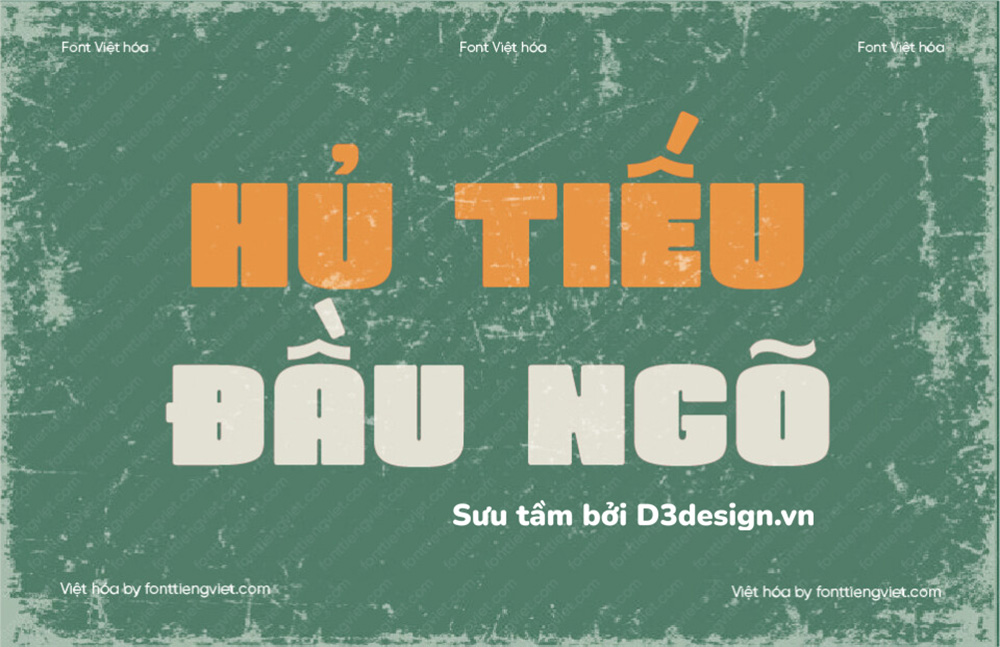
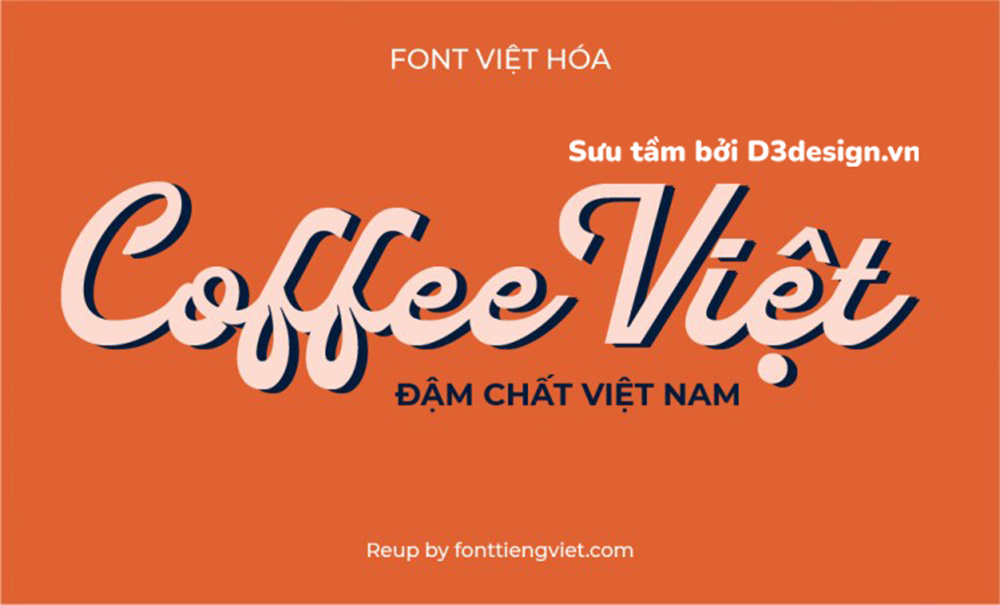
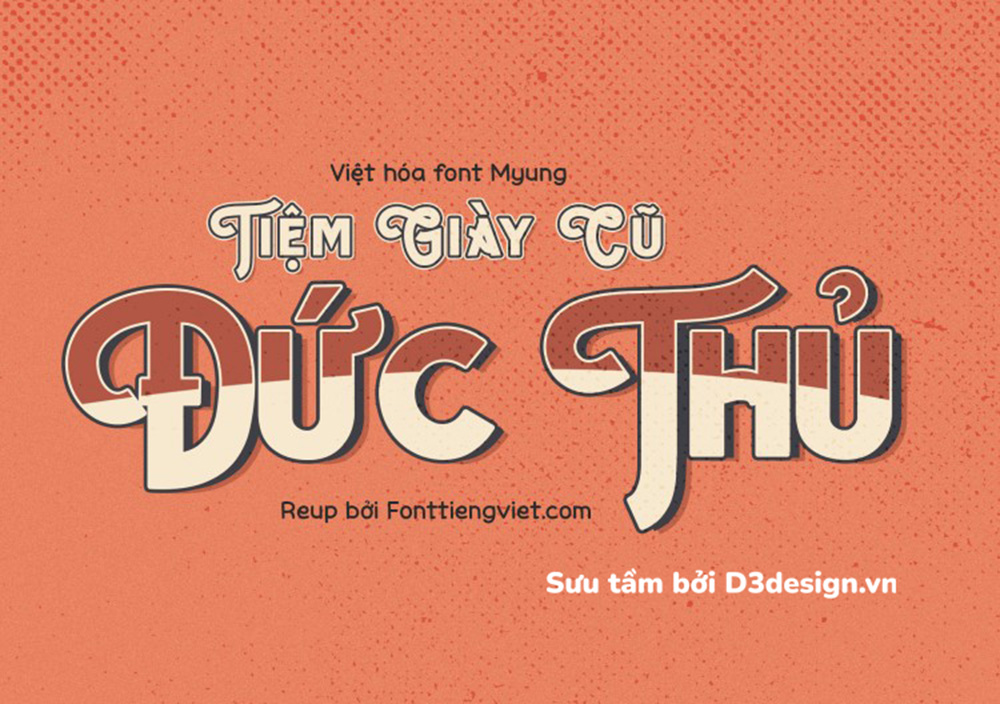
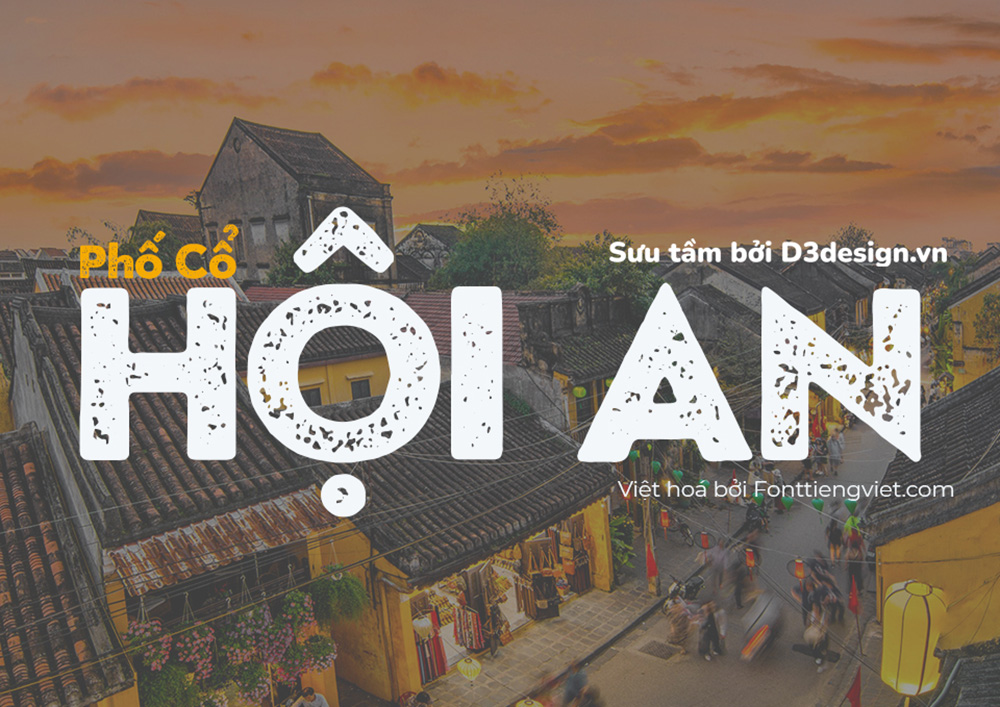
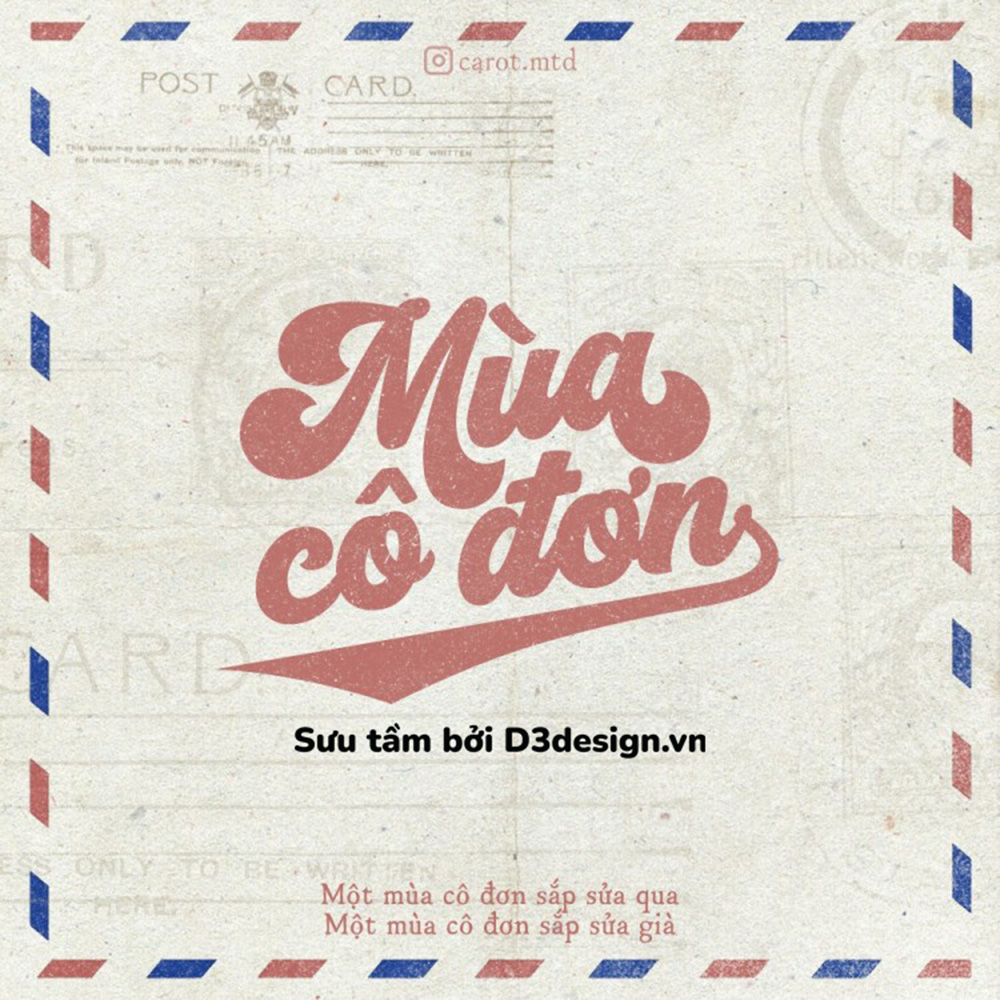
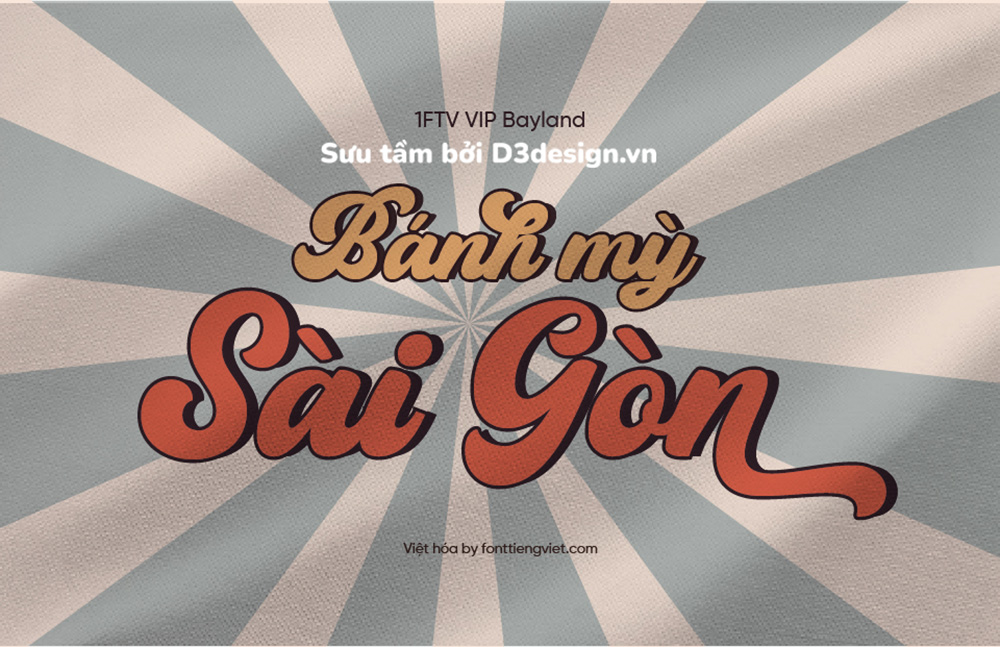
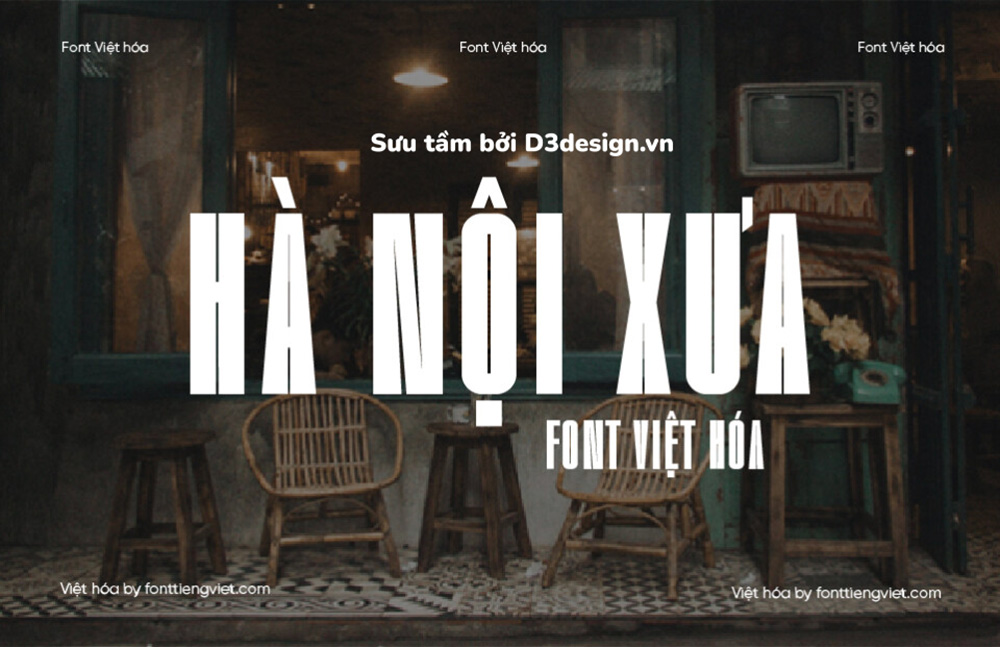
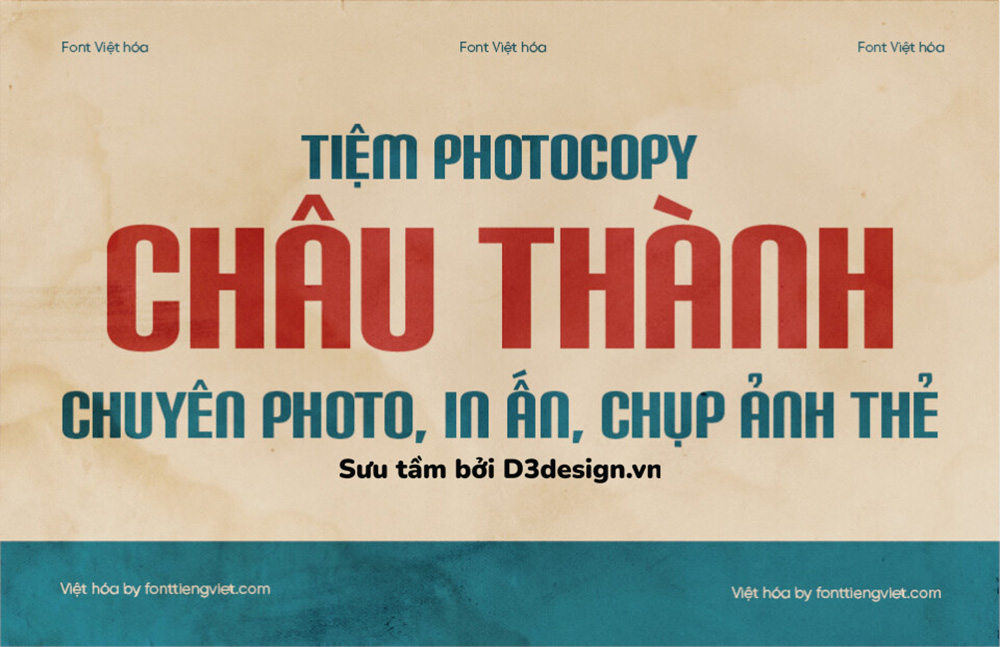
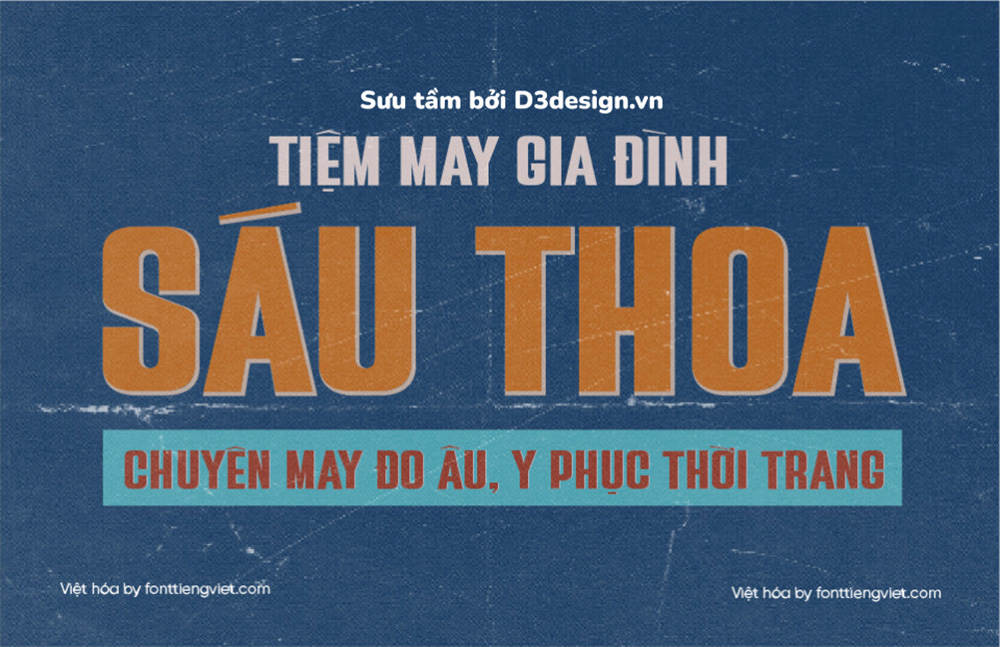
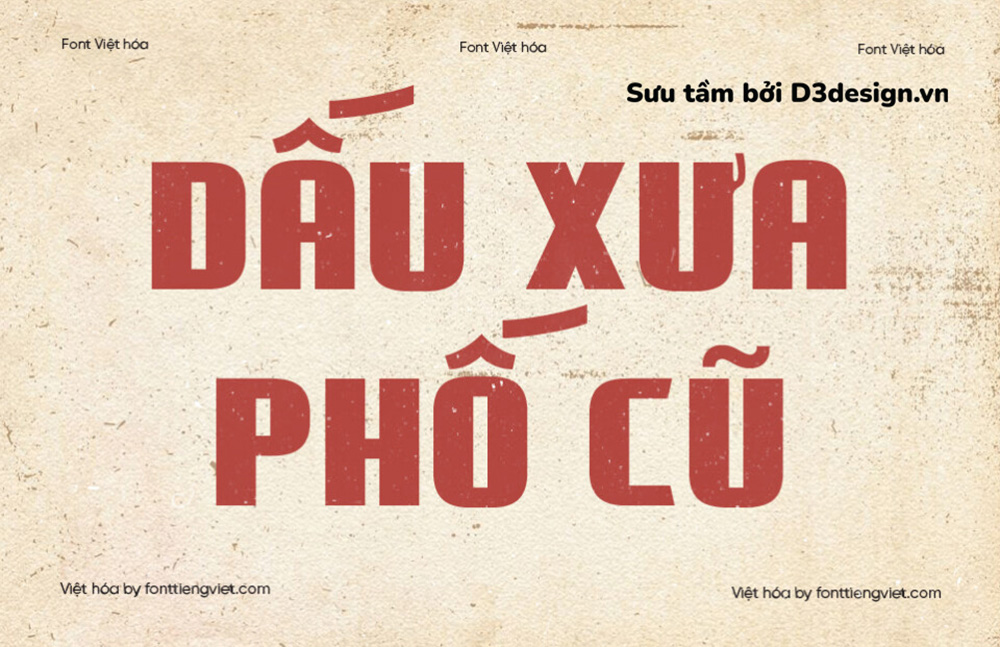
Tải 10+ Font Chữ Việt Hóa Phong Cách Xưa, Hơi Thở Hoài Cổ Dành Cho Designer